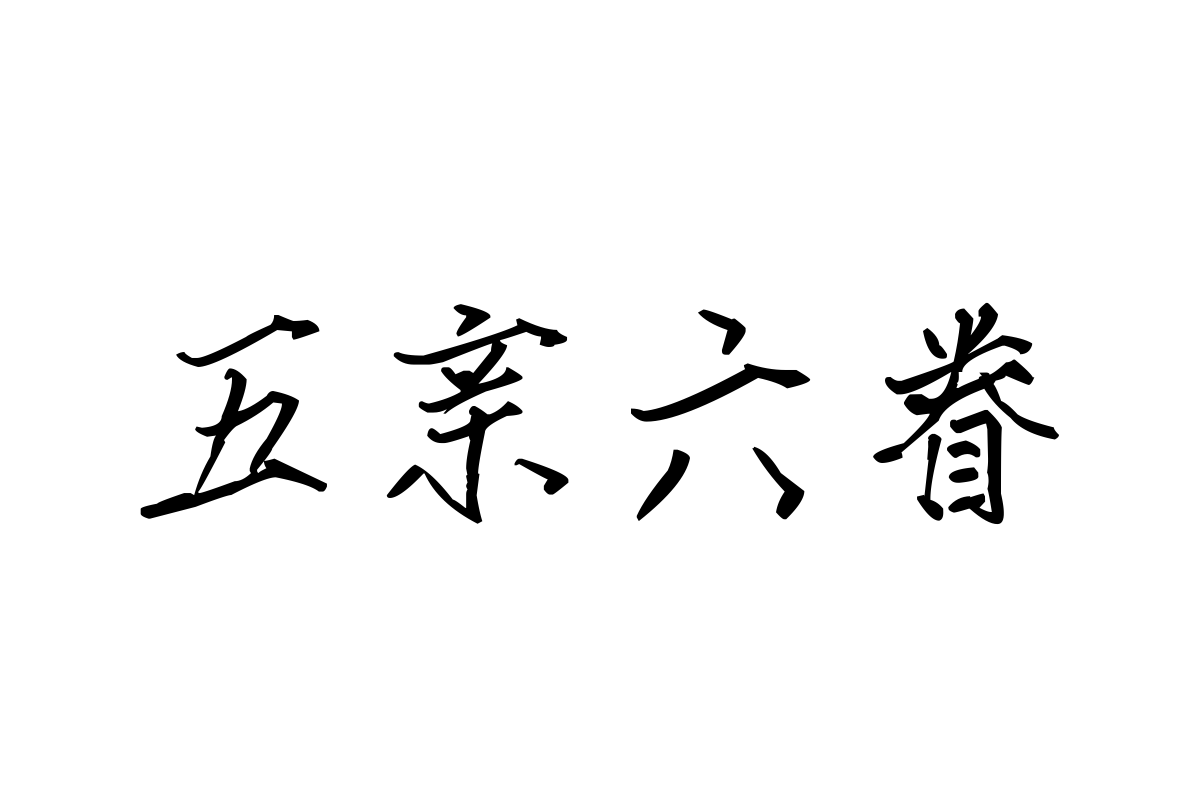
汉标瘦金体,又称“瘦金书”,是一种汉字书法字体。它起源于唐代,流行于宋代,是中国古代书法艺术的瑰宝之一。汉标瘦金体的笔画粗细适中,结构紧凑,线条流畅,具有很高的艺术价值和观赏价值。
汉标瘦金体的特点如下:
1. 笔画粗细适中:汉标瘦金体的笔画粗细适中,既不过于细长,也不过于粗大,给人一种平衡和谐的感觉。
2. 结构紧凑:汉标瘦金体的字形结构紧凑,笔画之间相互呼应,形成了一种独特的视觉效果。
3. 线条流畅:汉标瘦金体的线条流畅,无论是横画、竖画还是撇画、捺画,都呈现出一种优美的弧度,给人以美的享受。
4. 富有变化:汉标瘦金体在笔画、结构和布局等方面都表现出了丰富的变化,使得整篇作品既有统一性,又有多样性,具有很强的艺术表现力。
5. 易于书写:汉标瘦金体笔画清晰,结构稳定,易于书写和掌握,适合初学者学习和练习。
总之,汉标瘦金体是一种极具艺术价值的字体,它以其独特的风格和韵味吸引了无数书法家和爱好者的关注和喜爱。